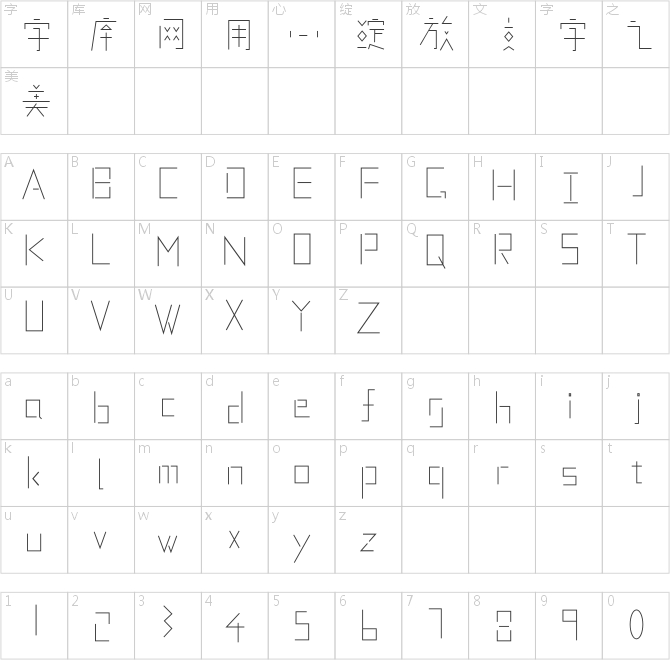
字体名称: 佛君城建体
作品以线条为缘起,以抽象几何手法,构筑极简唯美的城市建筑意象,除横平竖直的基础表现,融入45度斜角展开的线条,在保证识别性的基础上减化笔画,归纳出易于表现为几何造型的结构,形成结构独特、识别效果突出、极具时尚感的字型,契合互联网时代个性鲜明的传达需求,提供独具一格的视觉传播解决方案。